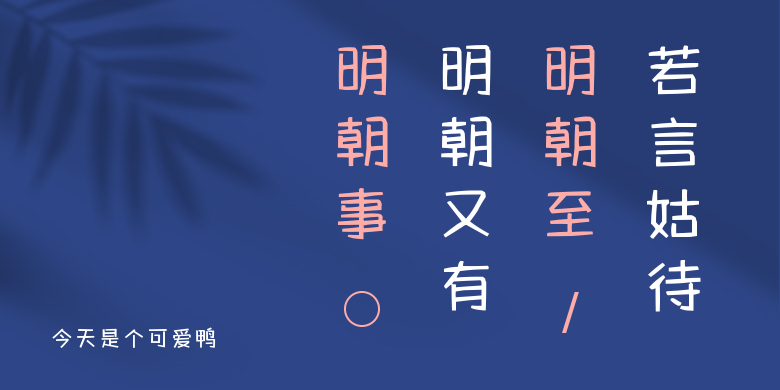
今天是个可爱鸭
今天是个可爱鸭,这款字体结构工整、笔画清晰,兼顾美观与易读性,适用于标题、正文、海报、包装、LOGO 等多种场景。字形优雅稳定,风格百搭耐看,适配日常排版与创意设计,让文字呈现更舒适、更具质感。今天是个可爱鸭一笔一画,皆是细节,以均衡的比例、流畅的线条打造舒适视觉体验,字形端正大气,风格简约现代。无论是商业设计、品牌宣传还是日常排版,都能轻松驾驭,让文字更有格调与力量。今天是个可爱鸭字体下载。